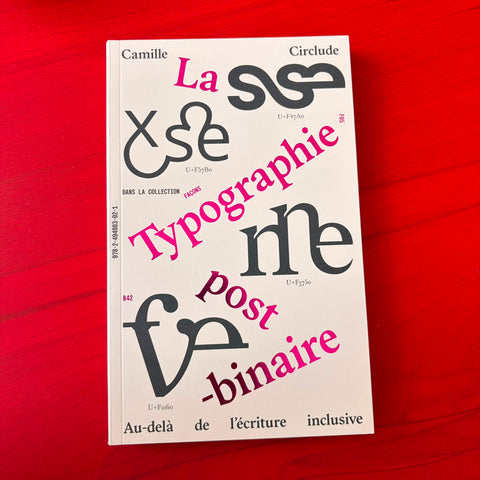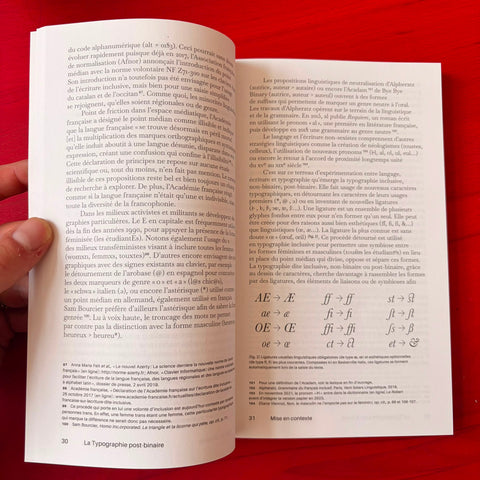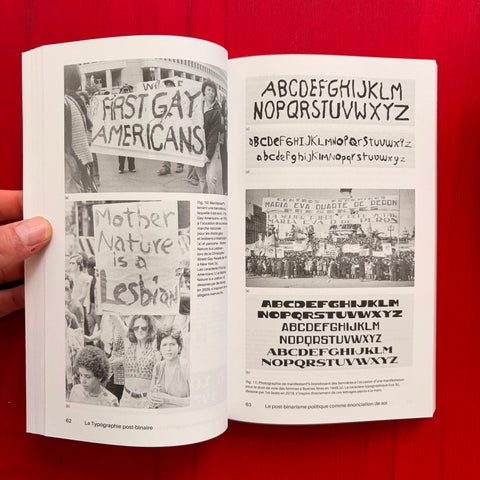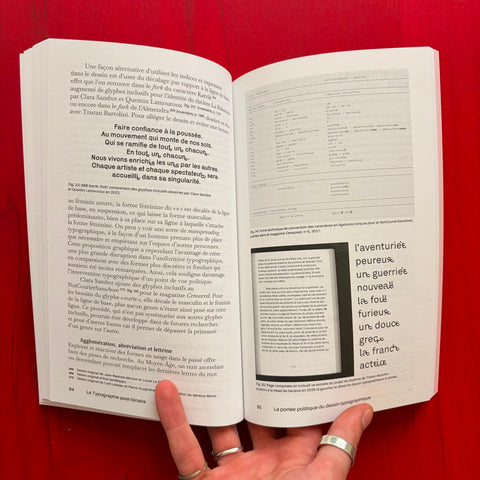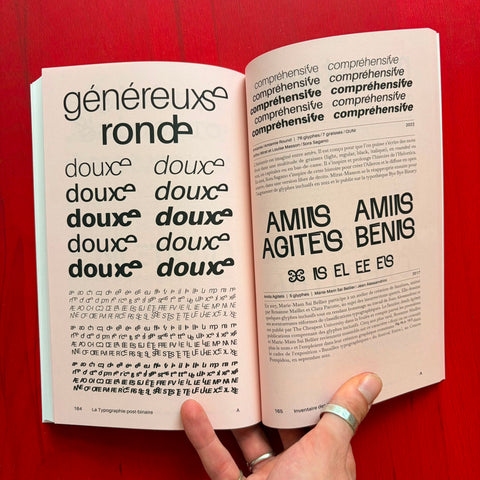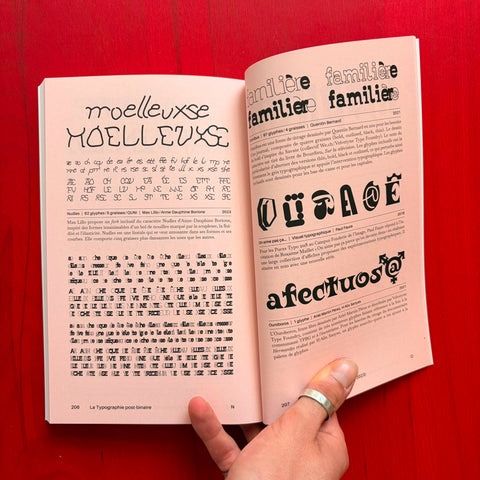
La typographie post-binaire: Au-delà de l'écriture inclusive / Camille Circlude
Comment dépasser la binarité de genre caractéristique de la langue française ? Cet ouvrage recontextualise l’apparition de l’écriture inclusive, questionne ses usages et recense les multiples alternatives possibles apparues depuis de nombreuses années. Si l’écriture inclusive et le « fameux » point médian ont ouvert la voie vers l’égalité des genres, il leur est aujourd’hui régulièrement reproché de reconduire cette binarité. Des initiatives portées par des dessinateur·ices de caractères typographiques offrent des espaces inédits afin de dépasser les hiérarchies de genre et les impensés théoriques tacitement induits par l’écriture inclusive. L’analyse historiographique de ces nouvelles formes typographiques apparues dans ce contexte a conduit Camille Circlude, membre fondateur·ice de la collective Bye Bye Binary, à considérer la portée politique du dessin typographique et l’a mené·e vers le concept de post-binarisme politique. La typographie est ainsi appréhendée comme une technologie émancipatrice permettant de résister à l’hégémonie et d’habiter l’hybridation des formes et des caractères. Le dessin de caractères typographiques inclusifs, non-binaires et post-binaires offre aujourd’hui la possibilité de matérialiser les existences queer, non-binaire, genderfluid, agenre et genderfucker dans ces espaces partagés et symboliques que sont la langue et l’écriture. Bien qu’il ne soit pas possible, ni souhaitable, de figer l’histoire de la typographie inclusive, Camille Circlude présente dans cet ouvrage un état des lieux de six années d’expérimentations (2017-2022) d’une pratique qui ne cesse de se propager, et qui continue de s’écrire au présent.